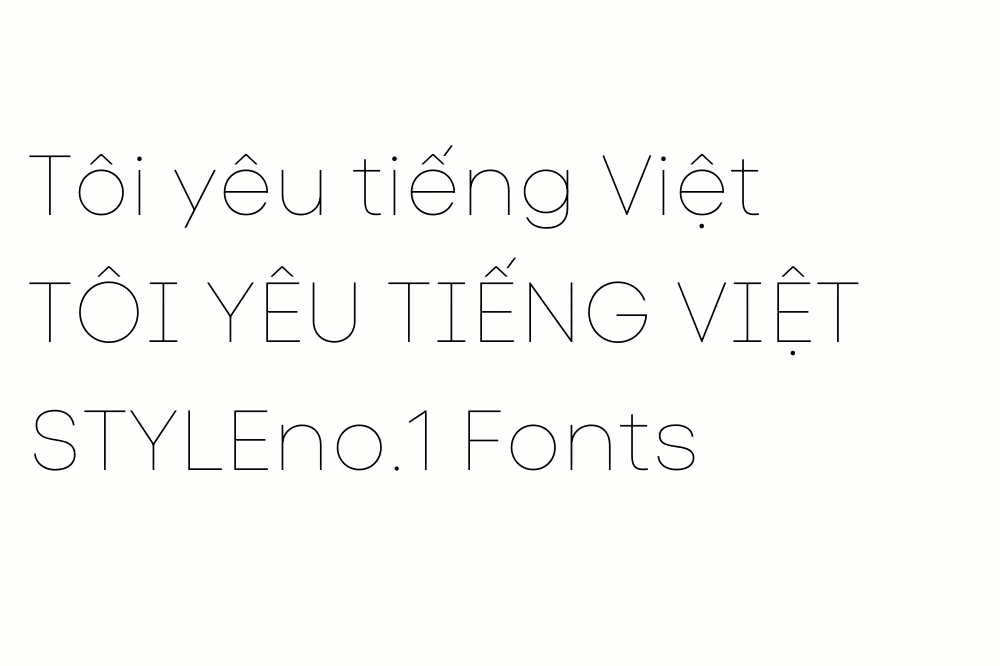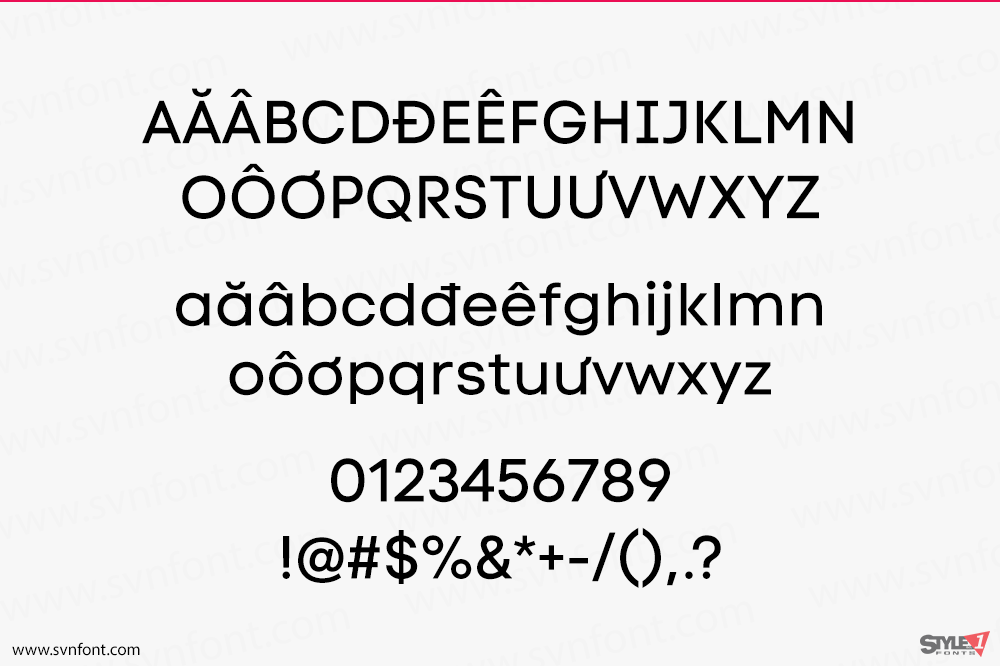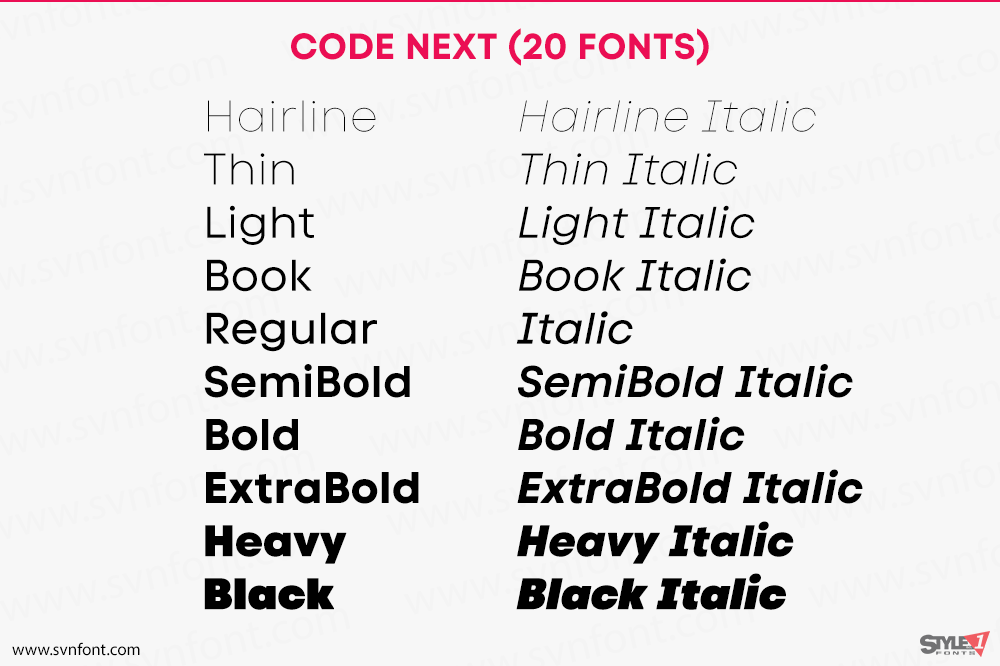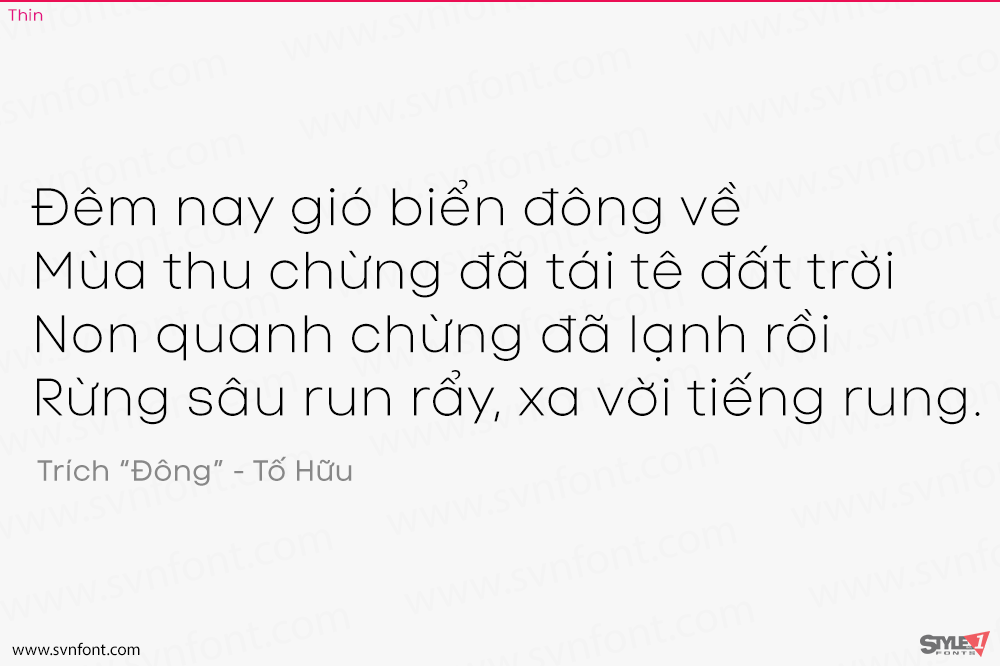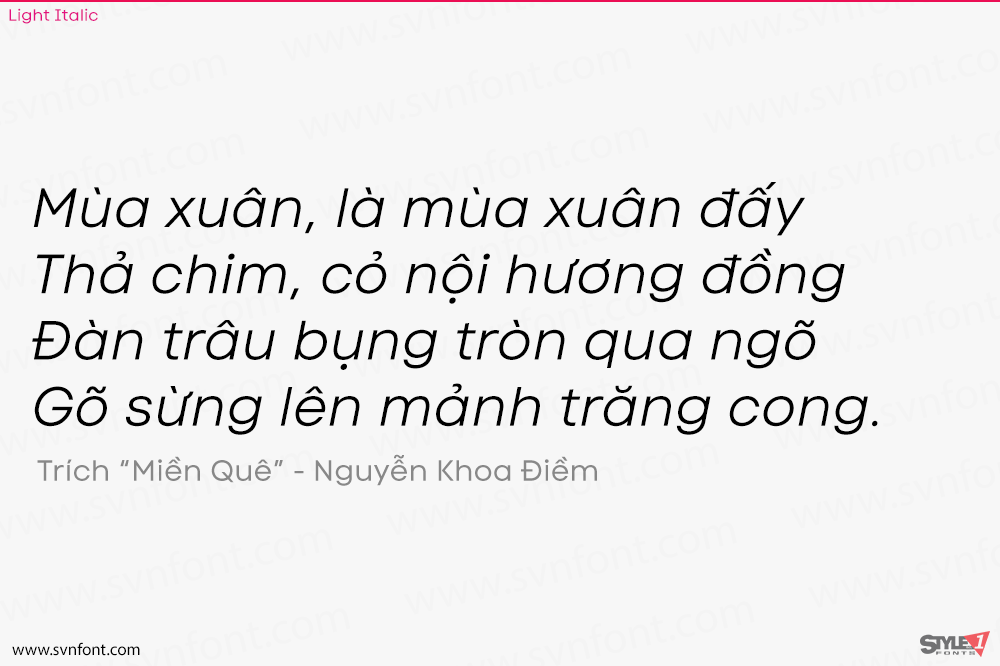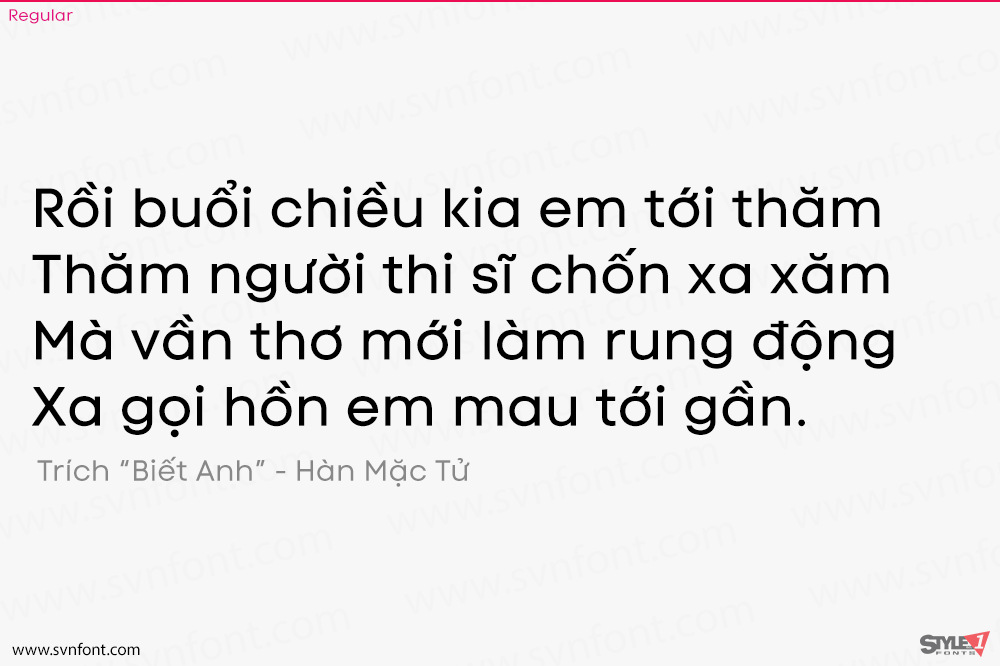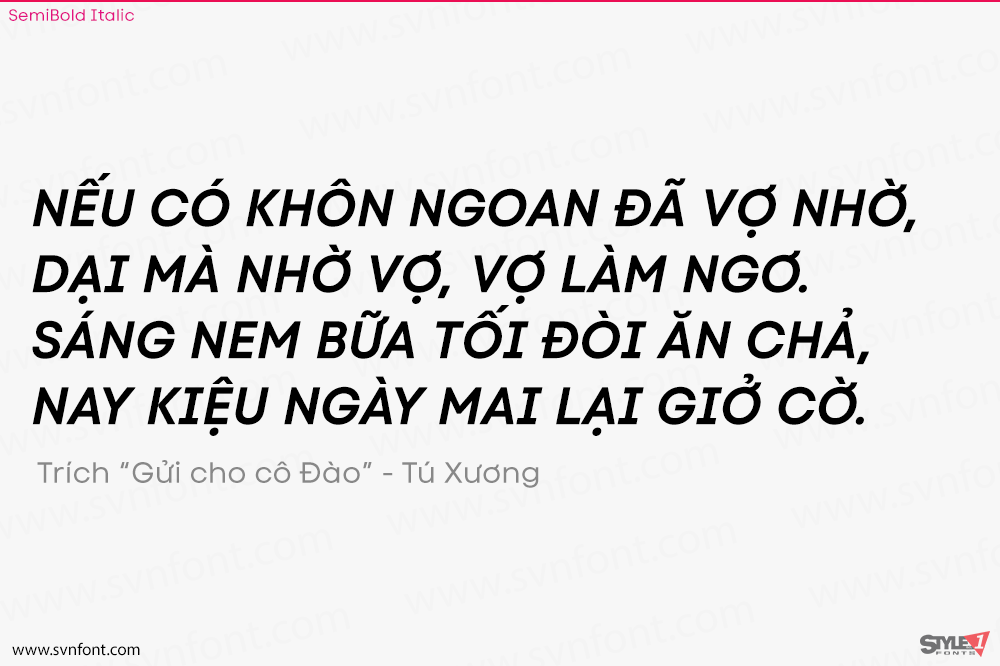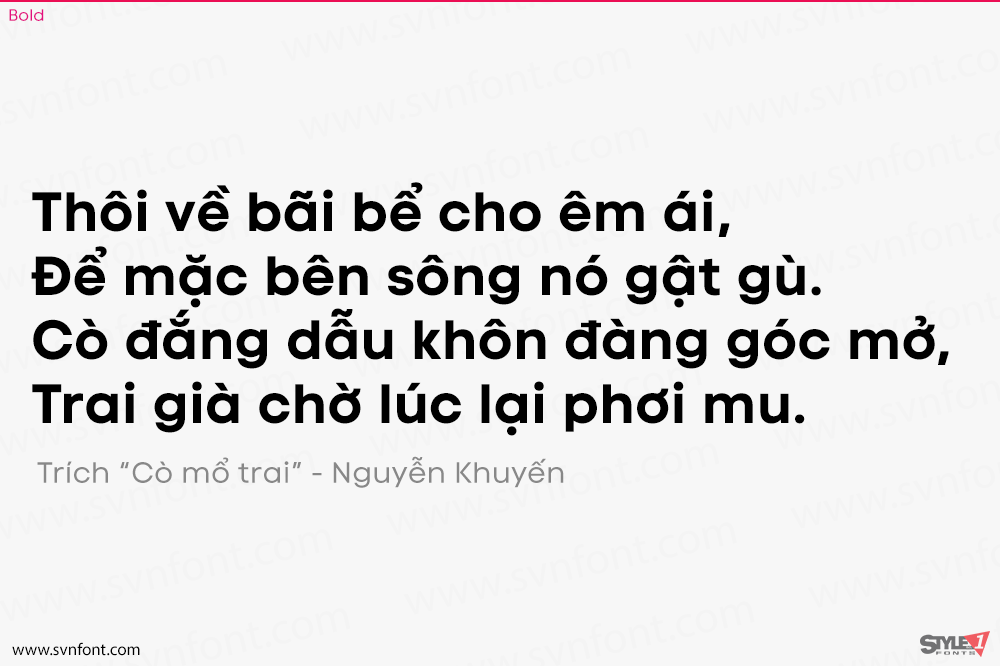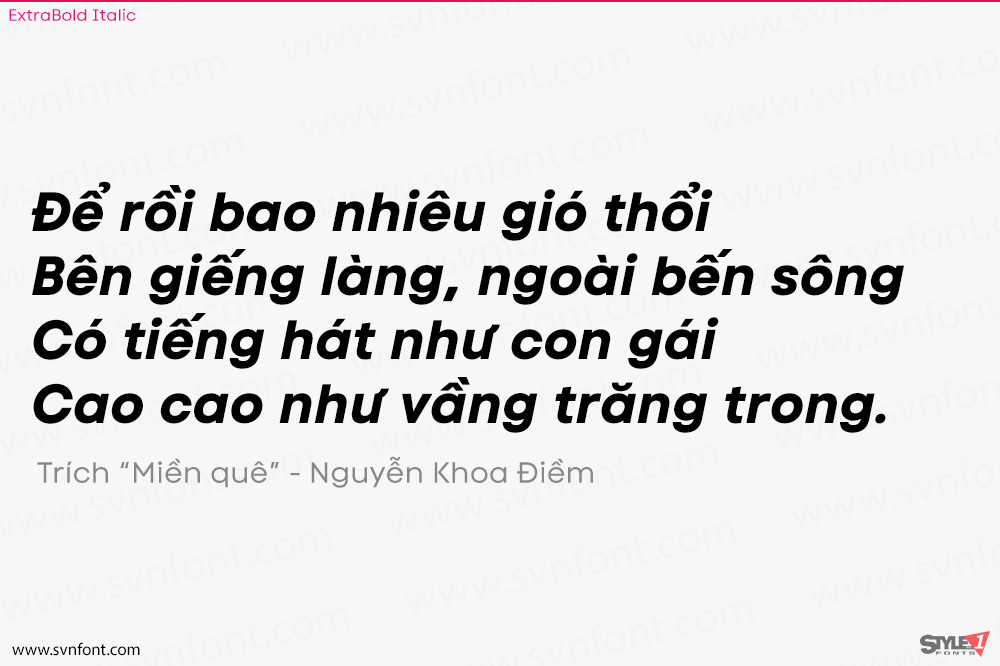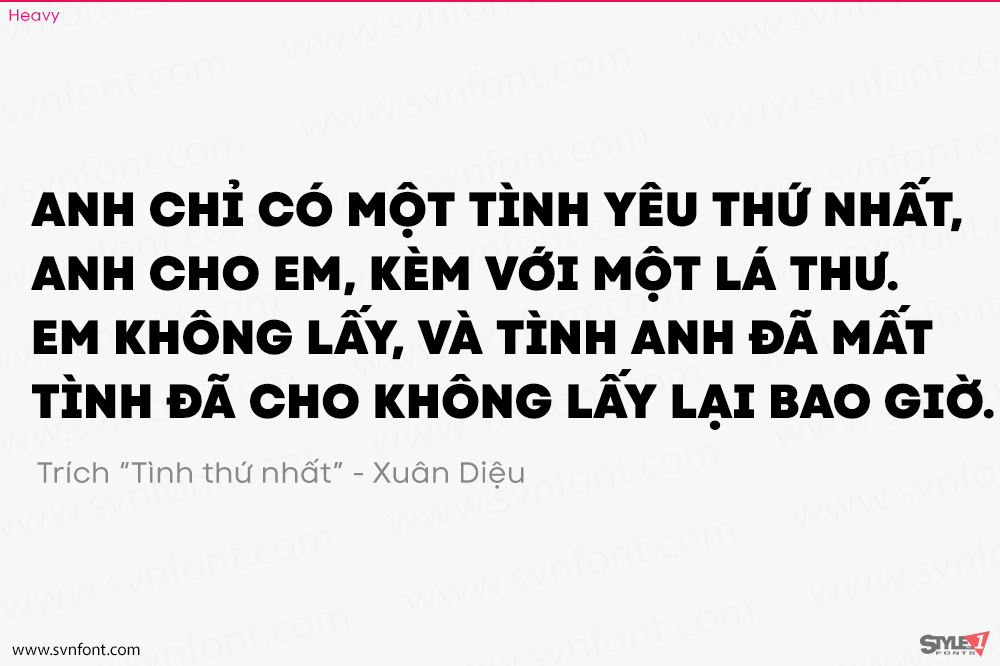
10 năm sau, một trong những kiểu chữ hình học đầu tiên trong danh mục của chúng tôi và là một trong những kiểu chữ yêu thích phổ biến của bạn đang vươn lên một tầm cao mới! Chúng tôi đang ra mắt bộ font độc lập Code Next — một sự tiến hóa đáng kinh ngạc từ Code Pro về chức năng, tính linh hoạt và ứng dụng. Sự chuyển đổi này bao gồm 6 độ dày mới, 10 kiểu nghiêng (Italics) mới, hỗ trợ đầy đủ tiếng Cyrillic mở rộng và tiếng Hy Lạp, thiết kế lại hoàn chỉnh và tinh chỉnh các ký tự (glyphs), 2 font biến thể (variable fonts), và còn nhiều hơn nữa.Quay trở lại năm 2011, Code Pro lấy cảm hứng từ phong cách grotesque được thiết kế để bổ sung cho những tác phẩm đáng nhớ, tạo nên sự khác biệt. Cân bằng giữa sự cách điệu và đơn giản hóa, nó được mã hóa với giọng điệu riêng biệt của các hình dạng hữu cơ cơ bản để trường tồn theo thời gian. Chúng tôi không hề biết rằng, nó sẽ mở rộng và phát huy hết tiềm năng của một “font từ tương lai” như Code Next mới.
Ngày nay, với 22 kiểu dáng, bộ font sans serif hình học này củng cố sự phù hợp của nó và mang một vẻ đẹp cấu trúc mạnh mẽ thông qua các hình thức đơn giản hóa nhưng có nét độc đáo.Những kiểu chữ này phù hợp với mọi thiết kế hiện đại trong in ấn, web và hiển thị trực quan. Được phát triển để vượt trội hơn mong đợi, Code Next sẵn sàng cho các dự án đa ngôn ngữ với Latin mở rộng, Cyrillic mở rộng và Hy Lạp.
Khám phá sự linh hoạt của Code Next và thay đổi mọi thứ với sự trợ giúp của 2 font biến thể, hơn 1280 ký tự (glyphs), và một bộ tính năng OpenType mở rộng bao gồm chữ hoa nhỏ (small caps), nối chữ tiêu chuẩn và tùy ý (standard and discretionary ligatures), các ký tự thay thế theo ngữ cảnh và kiểu cách (contextual and stylistic alternates), các bộ kiểu cách (stylistic sets), các dạng nhạy cảm chữ hoa/thường (case sensitive forms) và nhiều hơn nữa.
Nhà thiết kế: Svetoslav Simov, Mirela Belova, Stan Partalev
Nhà phát hành: Fontfabric